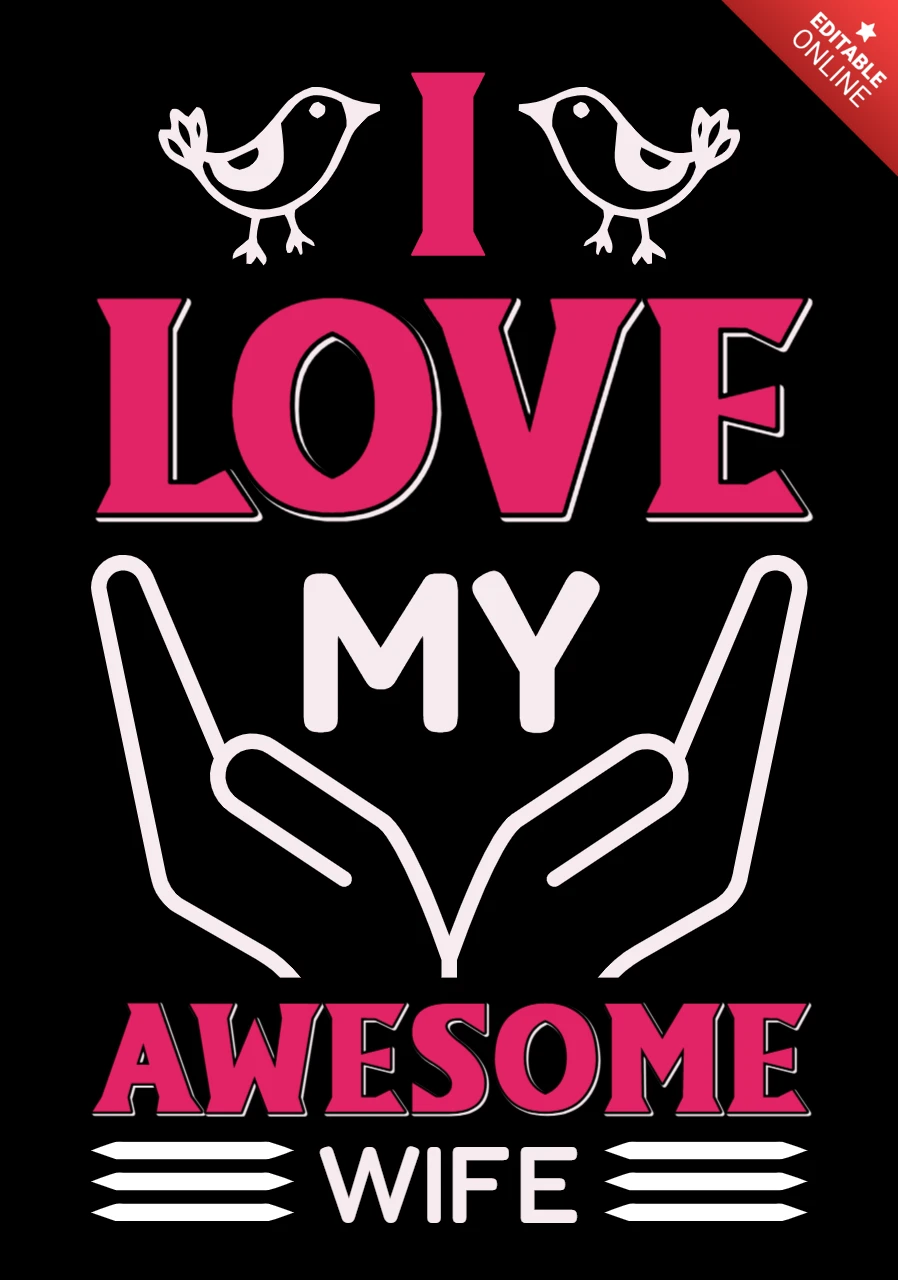
Love my awesome vrouw typografie ontwerpsjabloon
Bewerken in Design Studio Downloaden in JPGLaat je creativiteit de vrije loop met onze moderne ontwerpsjabloon, perfect voor kleding en speelse afbeeldingen die je liefde voor huisdieren laten zien, met gewaagde illustraties en oprechte quotes!